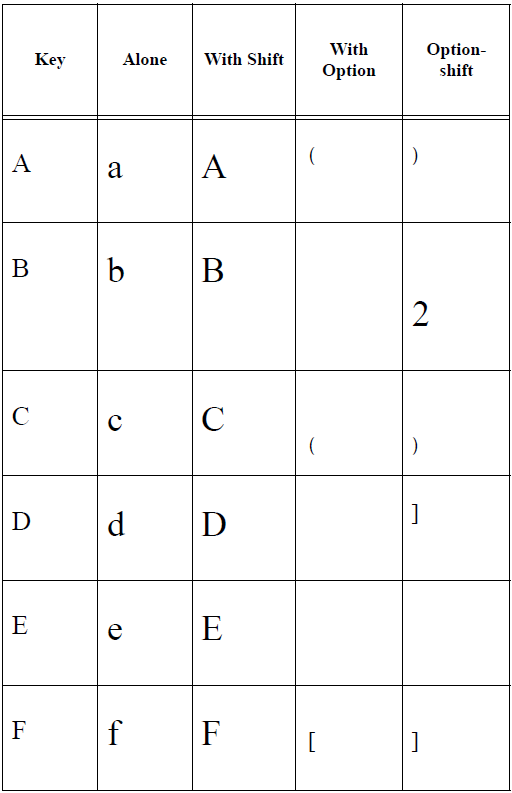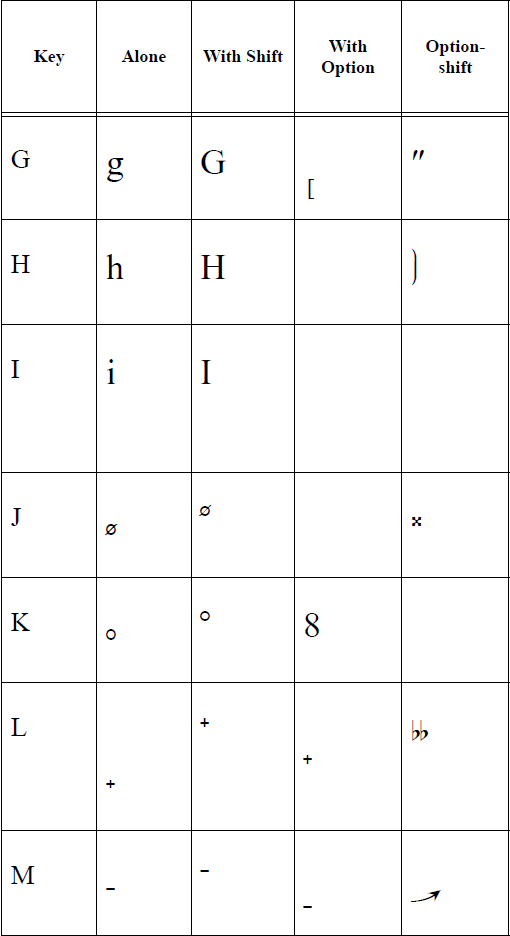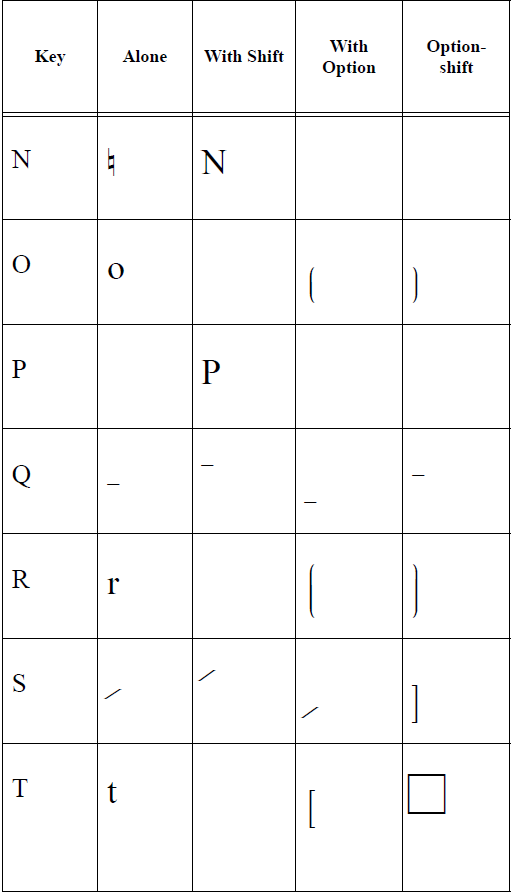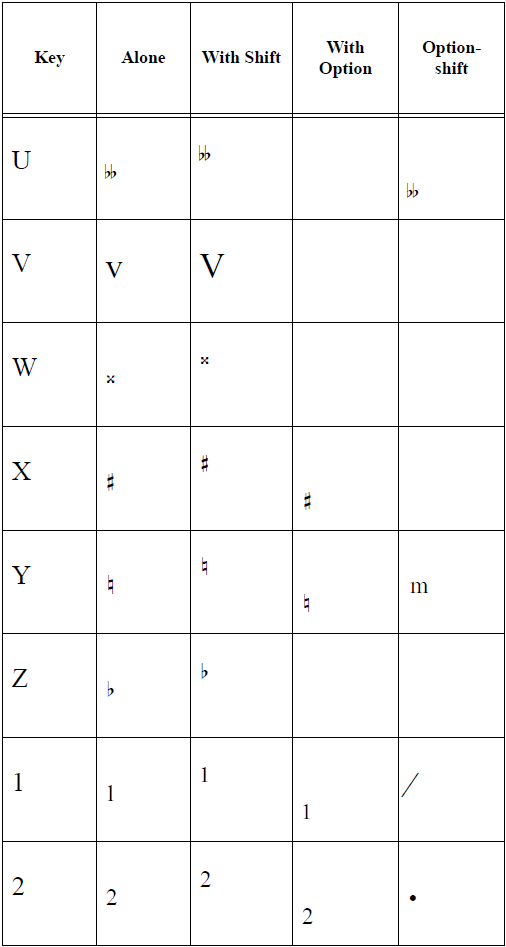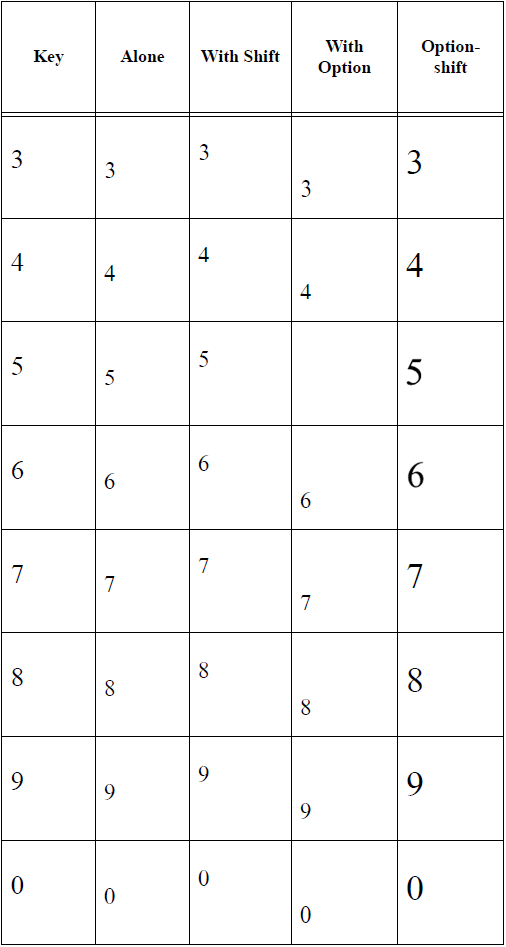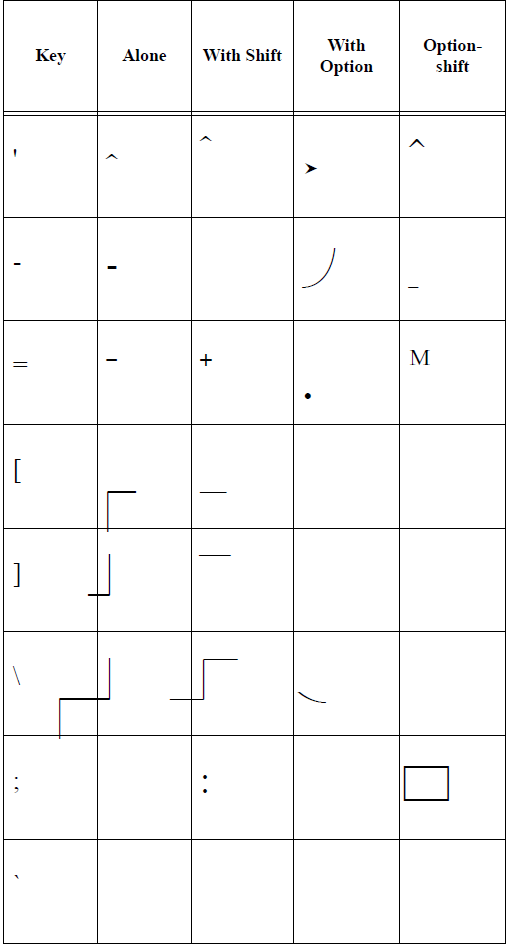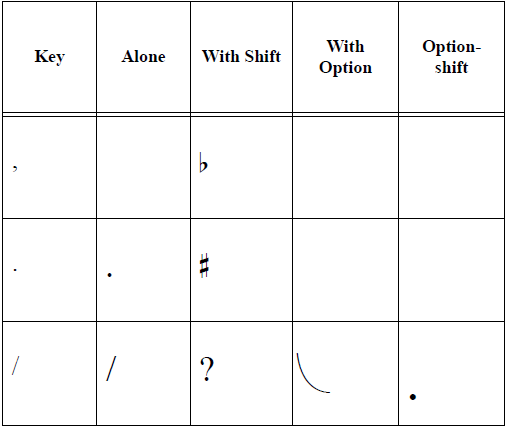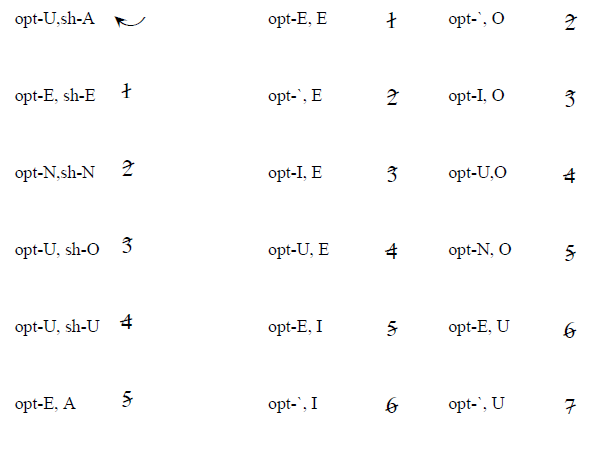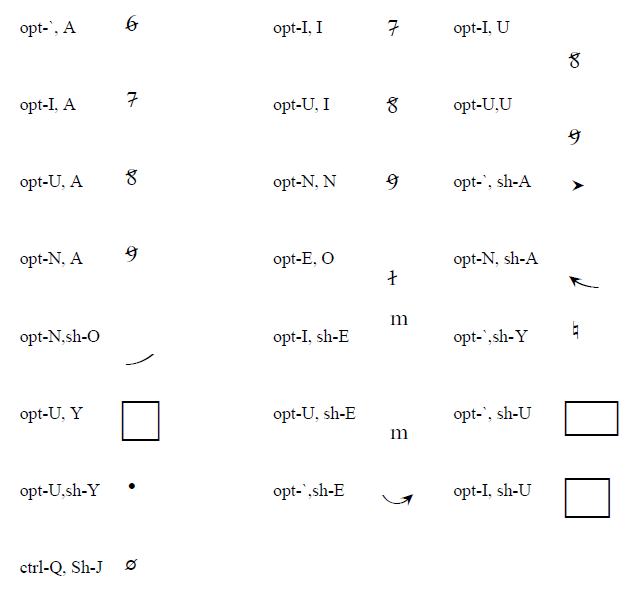
Il Fobnt Finale Numerics comprende tutti i caratteri necessari per la scrittura dell'analisi armonica e del basso cifrato. I caratteri ad ampiezza Zero vi permettono di creare colonne di caratteri, come previsto dalla prassi della scrittura dell'analisi armonica. Utilizzate lo Strumento Testo cantato per inserire la numerazione e la cifratura del basso e dell'analisi armonica. Per ulteriori dettagli, si veda Analisi armonica e Basso cifrato.
Note. In questi elenchi sono riportati la gran parte dei caratteri più utilizzati e le relative scorciatoie da tastiera.